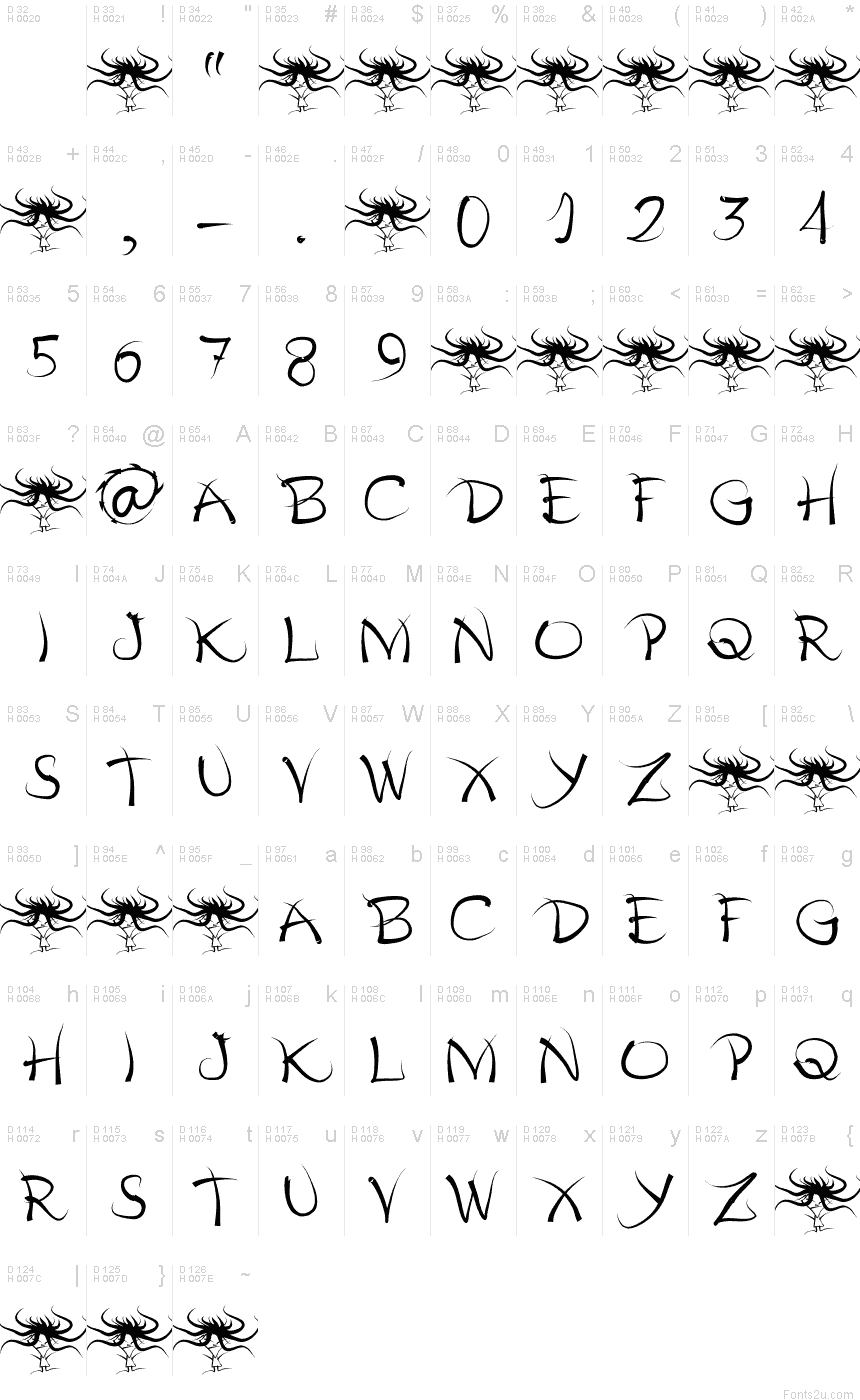
Pelos من تصميم Lagalga هو خط مجاني مكتوب بخط اليد يبدو كحروف كُتبت بحبر مبلل باستخدام فرشاة سريعة. تتلوى الضربات العالية والرفيعة وتندفع عند الأطراف، مما يمنح كل كلمة طاقة جامحة ومتحررة. التباعد يبدو مريحاً وهوائياً، مما يجعل الحروف تتنفس مع الحفاظ على تماسكها كشعار نصي مميز ومعبر.
يتألق خط Pelos على أغلفة كتب الفانتازيا، وشعارات الفرق الموسيقية، وتغليف المنتجات الجريء، وتصاميم الهوية البصرية الغامضة أو السحرية، وعناوين الألعاب، والملصقات الدرامية. تضفي منحنياته غير المنتظمة توتراً فنياً يدوياً يجذب العين، خاصة عند استخدامه بأحجام كبيرة حيث تظهر ملمس الحبر بوضوح. للحصول على تنسيق متوازن، قم بدمج Pelos مع خط أساسي بسيط ومحايد (sans serif) للنص الرئيسي، واترك هذا الخط اليدوي يتولى العناوين والشعارات.